제3회 폰트페스티벌에 다녀오다
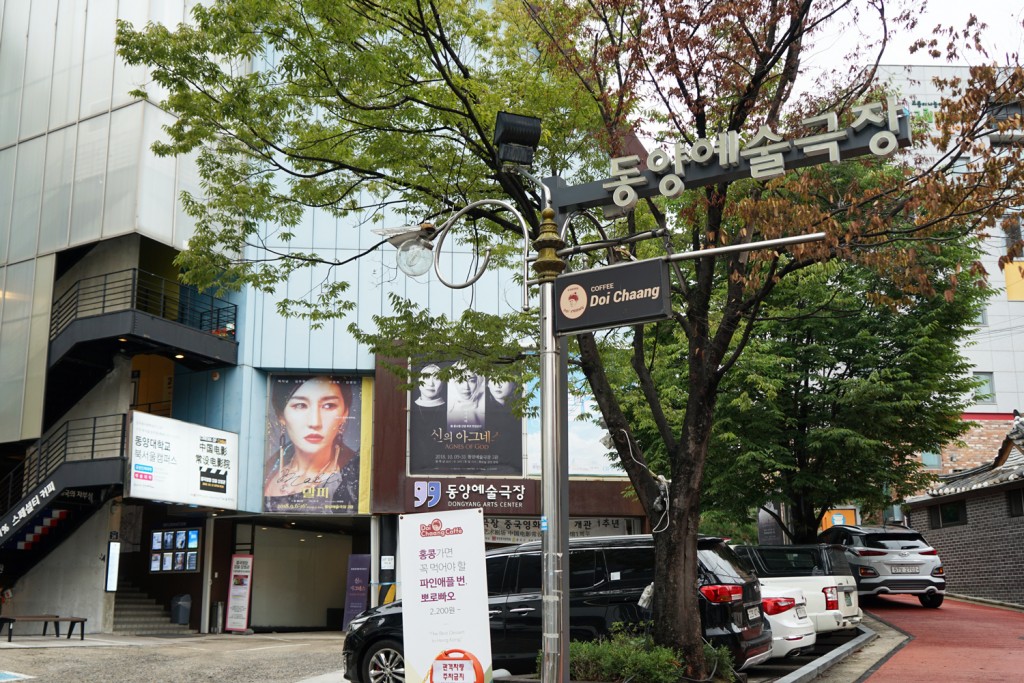
한국폰트협회에서 주최하는 제3회 폰트페스티벌이 지난 9월 20일 대학로 동양예술극장 2관에서 열렸다. 행사는 총 세 시간 동안 3부에 걸쳐 대화, 발표, 좌담의 순서로 진행되었다.
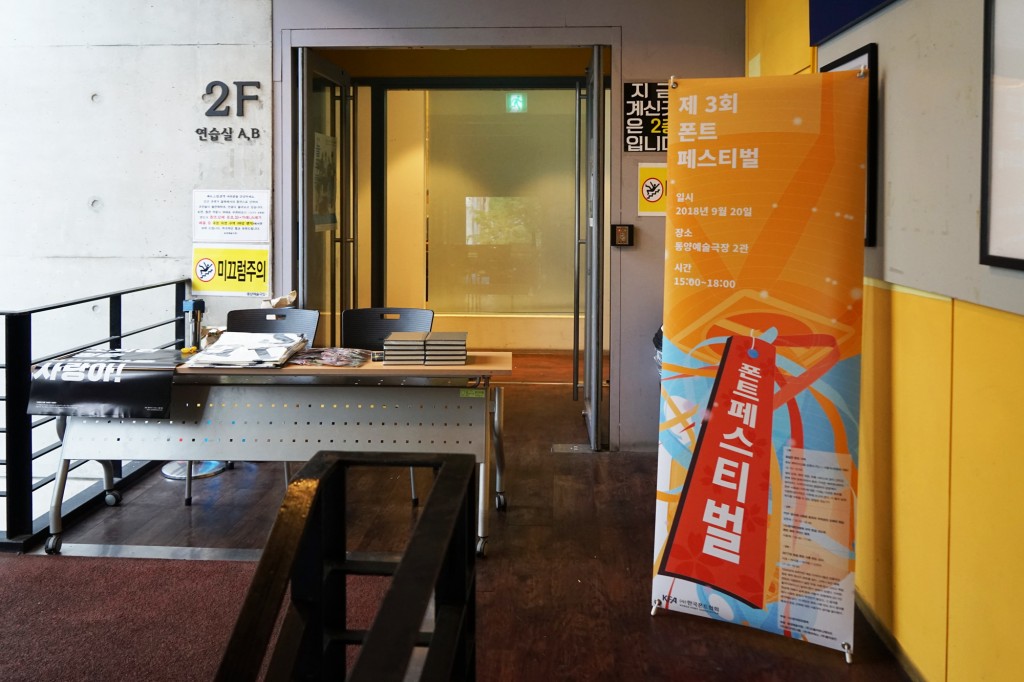
대학로의 한적한 골목에 있는 동양예술극장 2층에서는 행사가 시작되기 전 책, 에코백, 포스터 등 각종 후원 물품을 참석하는 사람들에게 나눠주고 있었다. 폰트 페스티벌은 누구나 참가비 없이 참여할 수 있었으며, 업계 종사자뿐만 아니라 디자인에 관심이 많은 학생들도 눈에 띄었다. 전체 참석자 수는 약 30여명 정도였다.
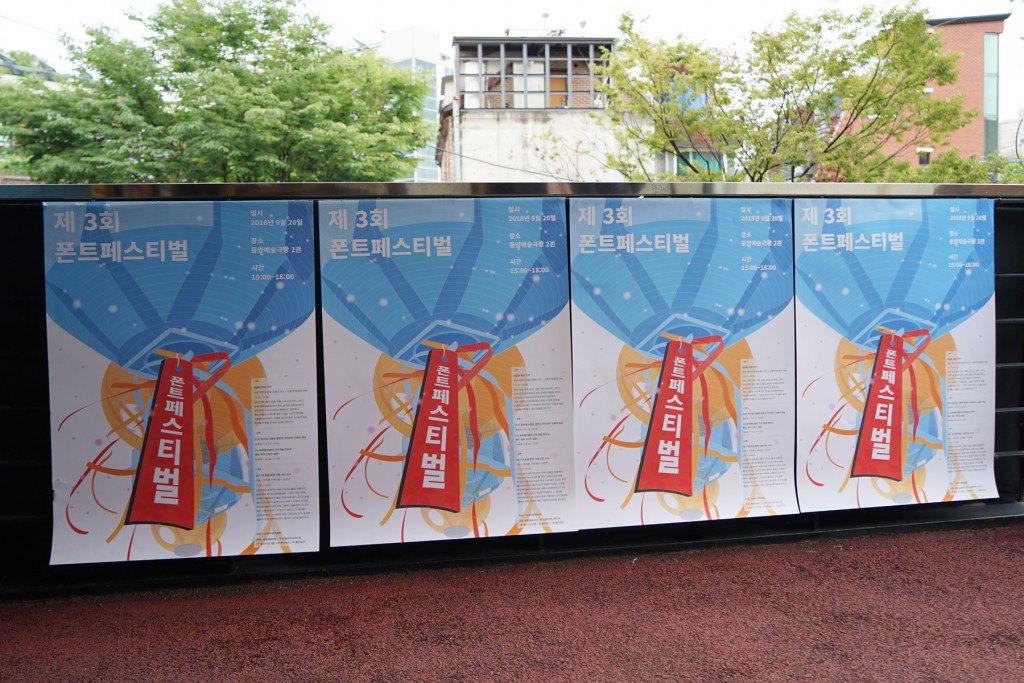
행사를 시작하기에 앞서 폰트협회 관계자는 “폰트 페스티벌은 매년 폰트를 사용하는 대중들과 접점을 만들기 위해 개최하고 있다. 논의되는 내용이 잘 정리되어 업계 사람들과 폰트를 이용하는 사람들에게 공유될 수 있는 자리가 되었으면 좋겠다”라며 행사 취지에 관해 설명했다.
#1부
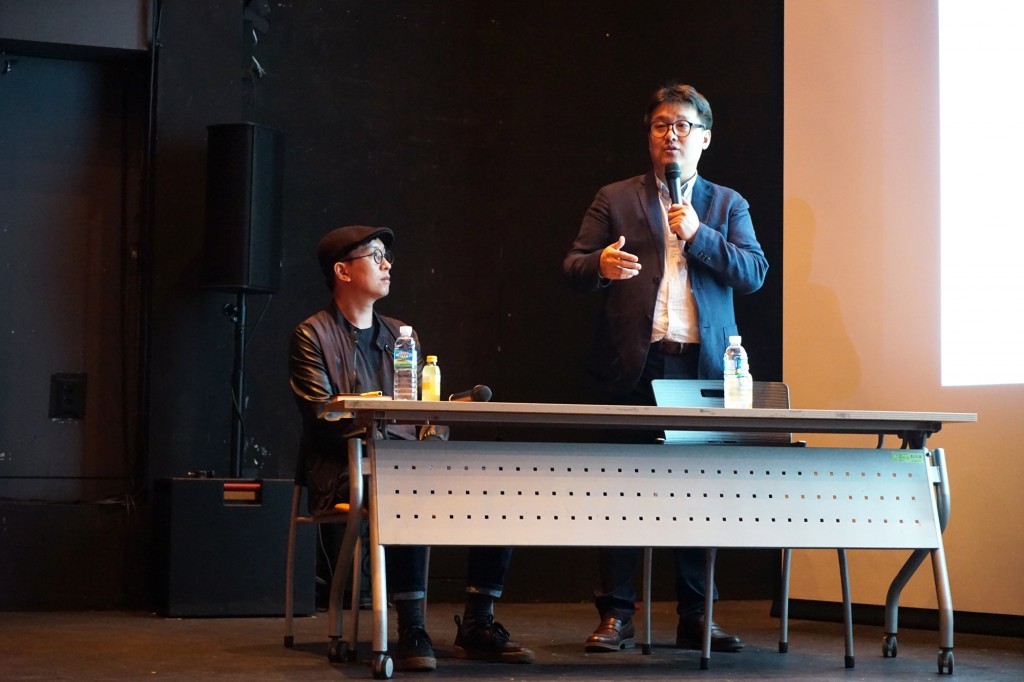
1부는 ‘폰트 제작 비용: 꿈같은 폰트 가격’이라는 주제로 폰트 사용자와 제작자의 입장을 각각 들어볼 수 있는 자리였다. 먼저, 폰트 제작사 입장은 산돌커뮤니케이션의 김병오 PD가 맡았다.
김 PD는 기업이 가격을 책정하는 방법과 소비자 가격을 결정하는 과정에 대해 세부적으로 다뤘다. 인상적이었던 부분은 실제로 디자이너가 한글 폰트를 만드는데 소요되는 시간으로 임금을 계산해본 것이었다. 보통 폰트 1종을 만드는데 한글 2,350자, 영문 94자, 특수문자 980자를 제작한다고 했을 때, 총 기간은 6개월이 걸린다. 영업일 기준 120일로 하루 8시간 근무했다고 하면 960시간이 소요된다. 960시간에 2018년도 최저시급인 7,530원을 곱하면 7,228,800원이라는 숫자가 나온다. 6개월에 7백만 원이라는 현저히 낮은 임금이 나온다. 그런데, 중급기능사 시간 평균임금인 19,825원으로 계산해보면 19,032,000원이 책정된다. 과연 이 임금이 타당한 것인지, 가격은 어떻게 책정해야 할지 사용자와 제작자 입장을 모두 고려하며 생각해볼 필요가 있다.
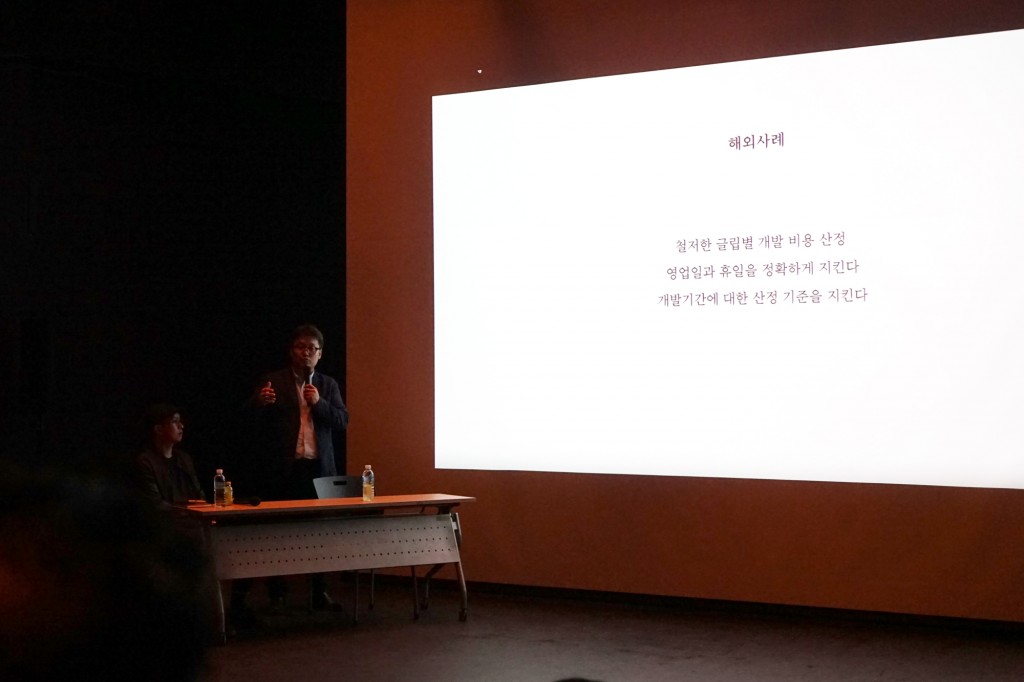
보통 해외 시장은 철저하게 글립별로 개발 비용을 선정하고 있다고 한다. 즉, 몇 글자를 만드는지에 따라 임금이 달라지는 것이다. 또한 영업일과 휴일을 정확하게 지키며, 개발 기간에 대한 산정기준도 지키고 있다. 그랬을 때, 디자이너의 삶의 질이 보장되고 더 질 좋은 디자인이 나오는 것이다.
사용자들이 여전히 폰트의 가격을 비싸다고 할 때, 김 PD는 ‘폰트를 만드는 목적’에 대한 고민이 필요하다고 했다. 폰트를 판매에 목적을 두고 만들었다면, 소비시장에 나온 하나의 제품이기에 수많은 고민과 시장분석, 타겟분석을 통해 잘 팔릴 수 있는 부분을 찾고자 노력해야 한다는 것이다. 결국, 폰트디자이너의 폰트가 노력한 만큼의 대가를 받을 수 있으려면 개인 디자이너는 시장에서 가치 있는 폰트가 될 수 있을지 고려해야 하며, 메이저 회사들은 사람들의 인식을 변화시키고 폰트의 가치를 높일 수 있는 다양한 활동을 꾸준히 하면서 동시에 디자이너의 처우에 관심을 가져야 한다고 말했다. 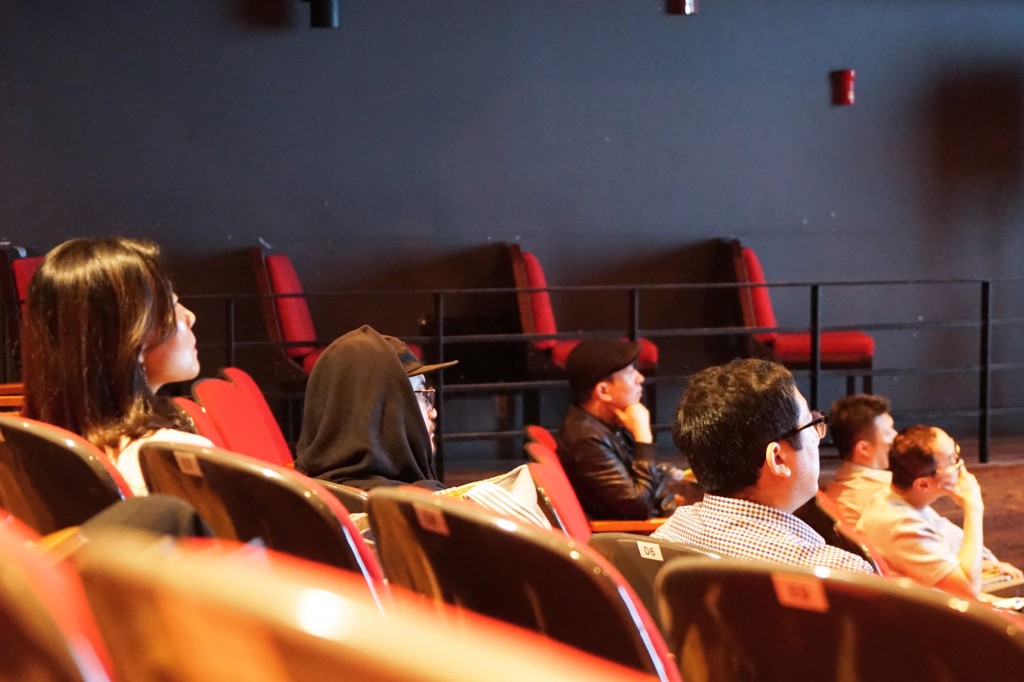
사용자 입장으로는 취그라프 스튜디오를 운영하는 최종원 대표가 의견을 전했다.
“보통 3명이 함께 디자인 작업을 하는데, 폰트가 필요한 경우 3벌을 함께 사야 한다. 그런데, 필요한 서체는 하나임에도 수백 개를 함께 구매해야 하는 경우가 많다. 시안이 채택될지 모르는 상황에서 폰트에 대한 비용을 많이 쓰는 게 부담스럽다. 영문 폰트의 경우 필요한 서체만 구매할 수 있어 가격 면에서 부담이 덜하다. 예를 들어, 어떤 폰트의 볼드체만 살 수도 있는 것이다. 반면 한글 폰트는 그렇게 구매하기가 쉽지 않다. 이런 부분이 힘든 점이다.”
최 대표는 폰트가격이 무조건 낮아지는 것은 원치 않는다고 했다. 폰트 디자이너들이 충분히 일한 만큼 돈을 잘 벌고 좋은 삶을 살 수 있어야 더 좋은 디자인이 나올 수 있다는 것. 개인적인 바람으로는 일반 대중들에게 폰트 정품을 써보는 경험을 하게 해주는 것도 필요하다고 전했다. 스탠다드, 프로버전이 있어 가격에 차등을 주거나 저렴한 가격으로 제공하게 되면, 사용자가 직접 써볼수록 점점 더 큰 가치를 원하게 되어 폰트 시장이 활성화되는 데 도움이 될 것이라고 말했다.
#2부
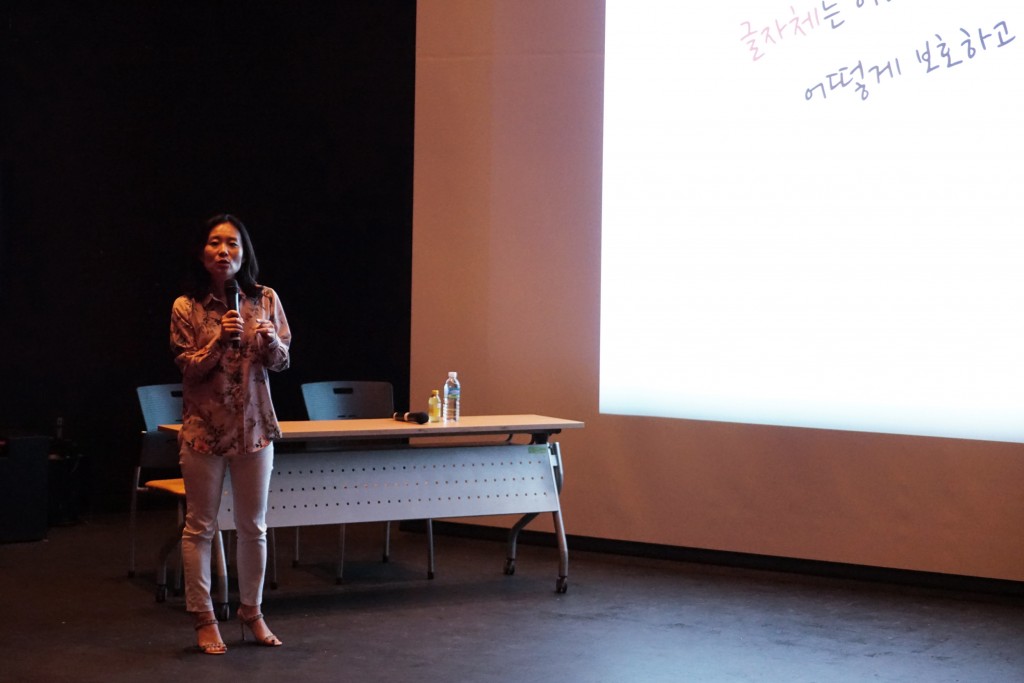
2부는 ‘PDF 문서에 사용된 폰트의 저작권의 오해와 현실’이라는 주제로 전(前) 한국소프트웨어저작권협회 연구소 소장이었던 김현숙 법학 박사의 발표가 이어졌다.
최근 들어 PDF파일에 사용된 폰트 저작권 분쟁에 대한 이슈가 논란이 많았다. 우선 결론적으로 이 문제는 판례가 없다. 그래서 더 어렵고 예민한 문제이지만 그는 차근차근 요점을 짚어 나갔다.
‘저작권’이란 타인에게 복제, 공연, 전시, 방송, 전송 등의 행위를 허락하거나 금지할 수 있는 권리를 의미한다. 현행법상 서체 도안은 디자인권으로는 보호받지만 저작권으로 보호받지 못하고 있으며, 서체 파일은 저작권 보호 대상이 된다. 따라서 폰트는 컴퓨터프로그램 저작물로만 보호가 가능한 상황이다.
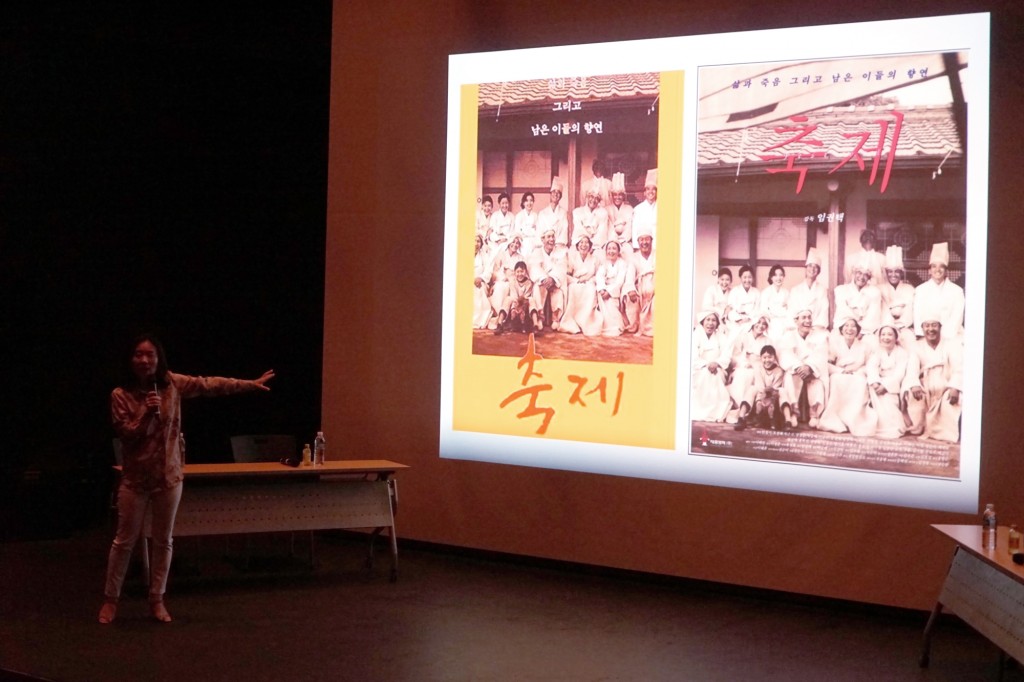
PDF 논쟁을 살펴보면, PDF 유형중 폰트파일을 내장하는 임베디드형 pdf파일의경우 문제가 생기고 있다. 문서를 열면 일시적으로 폰트가 포함된 문서를 보여주는 것인데, 이러한 pdf 파일을 인터넷에 게시했을 때 과연 폰트 저작권은 침해된 것일까?
결론적으로, 인터넷에 PDF파일을 게시했다는 것만으로 저작권 위반으로 처벌할 방법은 아직 없다고 한다. 하지만, 판결의 선례가 없으므로 확실한 답을 내릴 수는 없으며 만약 권리자가 임베디드형 PDF를 인터넷에 게시하면 안 된다고 약관에 명시했다면, 저작권 침해는 아니어도 계약을 위반한 경우가 될 수 있으니 유의해야 한다.
사용자의 입장에서 가장 확실한 방법은 이미지형 PDF로 업로드 하는 것인데, 이는 스캔한 문서처럼 도안은 살아있지만, 이미지라서 폰트가 포함되지 않기 때문에 저작권은 문제 되지 않는다. 하지만 PDF 문서의 호환성과 사용 환경을 고려했을 때 과연 효율적인 방법일까 싶다.
김 박사는 이 문제의 해결을 위해서는 법원의 판결이 필요하다고 한다. 사용자와 권리자가 실제로 판결을 거쳐 선례를 만들면 좋겠다고 제안했다. 단지 PDF에 사용된 폰트라는 이유만으로 저작권 침해를 다루는 것은 현실과 동떨어진 의견이기 때문이다. 또한, 문제의 근본적인 해결을 위해 실제 디자이너들이 관심을 두고 사용자와 권리자가 같이 고민해야한다고 역설했다.
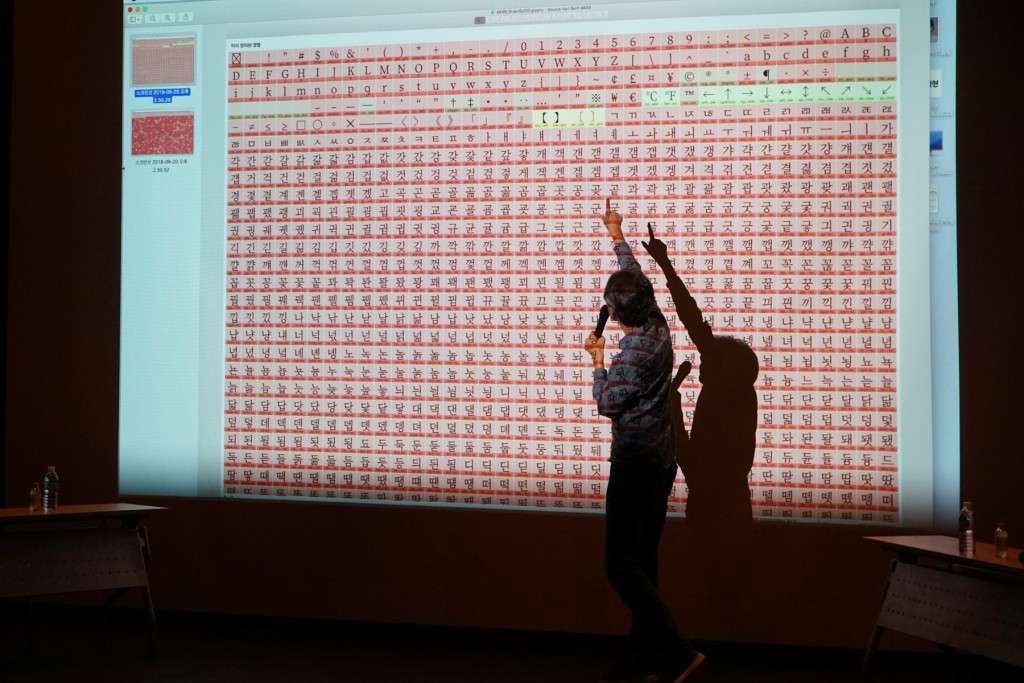
2부 말미에서는 ‘폰트협회 규격 한글 코드와 폰트 제작 가이드 발표’라는 주제로 이용제 교수의 발표가 이어졌다. 발표에서는 한글 폰트를 제작하는데 사용하는 규격을 새롭게 정비하고자 해당 작업을 시작했으며, 어도비의 규격과 차이가 난다는 점을 설명했다. 또한, 최종적으로는 입력기를 만들어 폰트 제작자들의 사용환경을 개선하고자 한다고 계획을 전했다.
#3부
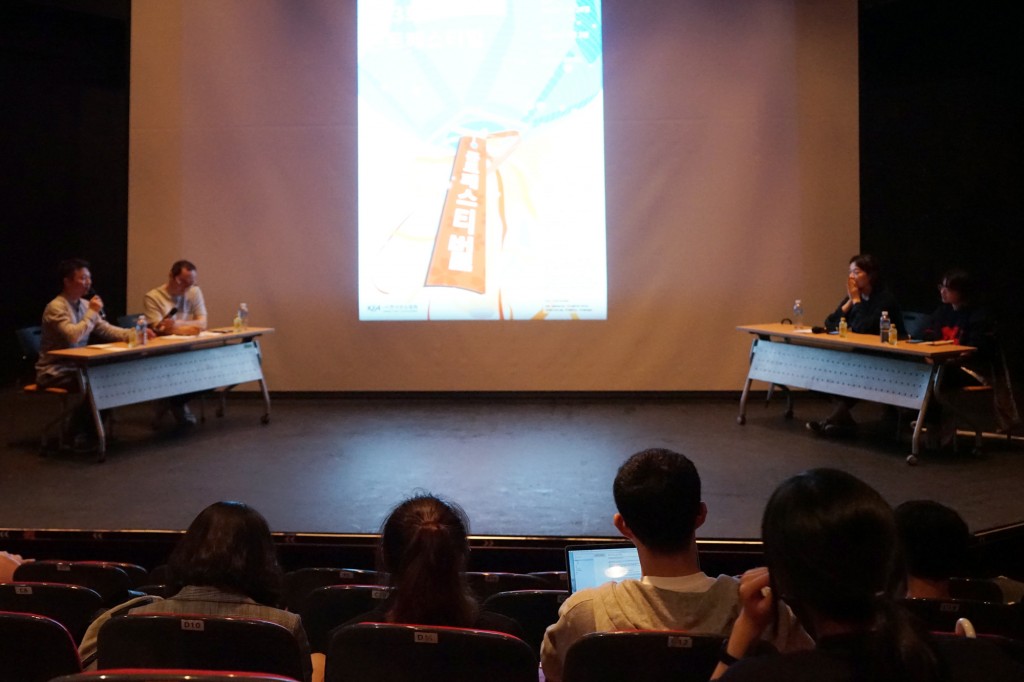
3부는 ‘2017년 한글 폰트 사용 빈도 조사’라는 주제로 좌담이 이어졌다. 타입 디자이너 이호, 박지훈 디자인의 대표 박지훈, 현대백화점 아트디렉터이자 그래픽 디자이너인 박이랑, 오늘의풍경 스튜디오 디자이너인 신인아가 좌담에 참여했다.
폰트 디자이너가 아닌 디자이너들이 어떤 폰트를 어떻게 사용하고 있는지 들을 수 있었다. 연령층과 디자인 분야를 다양하게 고려하여 30명의 사용자를 조사했고, 2017년 가장 많이 사용한 폰트가 무엇인지 물었고 그 결과를 아래와 같이 분석했다.
첫째, 응답자 중 가장 많이 사용한 폰트는 SM세명조와 같은 SM계열의 폰트였고 주로 출판사에서 많이 사용했다.
둘째, 무료 폰트의 사용빈도도 높았다. 법률적인 문제가 무서워 클라이언트가 처음부터 무료서체로 사용해달라는 요구도 많다고 했다.
셋째, 독립 활자 디자이너의 활약이 돋보인다는 점이다. 특히 젊은 연령층은 독립 디자이너의 폰트도 즐겨쓰고 있다. 디자이너의 개성이 잘 담겨있으면서도 조판했을 때, 문제없이 잘 읽힐만큼 개인 디자이너의 수준이 높아진 것이다.
넷째, 폰트 클라우드 서비스가 많아졌고 사용자 입장에서 저렴한 가격에 불편함 없이 여러 가지 서체를 골라 쓸 수 있어 좋다는 의견이 많았다.
박이랑 디자이너는 “우리가 노토산스를 많이 사용하지만, 정말 아름다운 폰트일까? 계속 쓰고 있지만 SM명조만 꼭 써야 할까?”라는 의문이 든다면서 습관적으로 폰트를 사용하기보다 의식적으로 새로운 폰트를 찾아보려 노력하고 있다고 의견을 말했다.
3부는 참석자들에게 한가지 방향으로만 이야기하지 않고, 질문을 받아 답변하는 시간도 마련되어 있었다. 사소한 질문이라도 좌담의 강연자들이 고민하여 진정성 있게 답해주었다. 하지만, 예정되었던 시간보다 행사가 길어지자 3부 중간부터는 자리를 점점 비우는 사람들이 많아졌다. 또한, 30명이라는 표본으로 조사한 결과를 일반화시키기에는 적은 수가 아니었을지 의문이 남는다.
폰트에 대한 최신 이슈를 살펴보고, 업계에서 일하고 있는 현장의 이야기를 들을 수 있었던 점은 이번 행사의 가장 큰 장점이었다고 생각한다. 그러나, 폰트협회 관계자들도 밝혔듯이 사전 홍보가 미흡해 참석자가 많지 않았다. 일반 대중에게 좀 더 다가가려는 노력이 있었으면 좋았을 것이라는 아쉬움이 남았다. 또한, 폰트 ‘페스티벌’이라는 이름과는 다르게, 폰트업계 종사자가 아니면 바로 이해하기 어려운 내용이 많았다. 내년부터는 대중의 눈높이에 맞춘 프로그램이 더해진다면 더 좋은 행사로 자리매김할 수 있을 것이다.